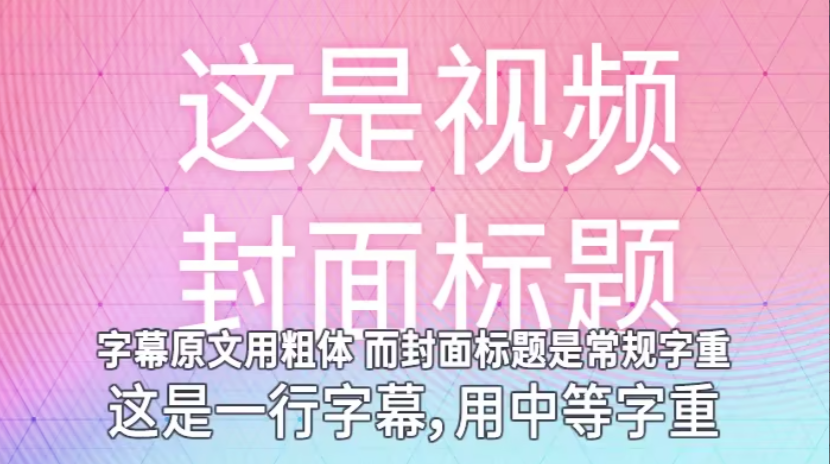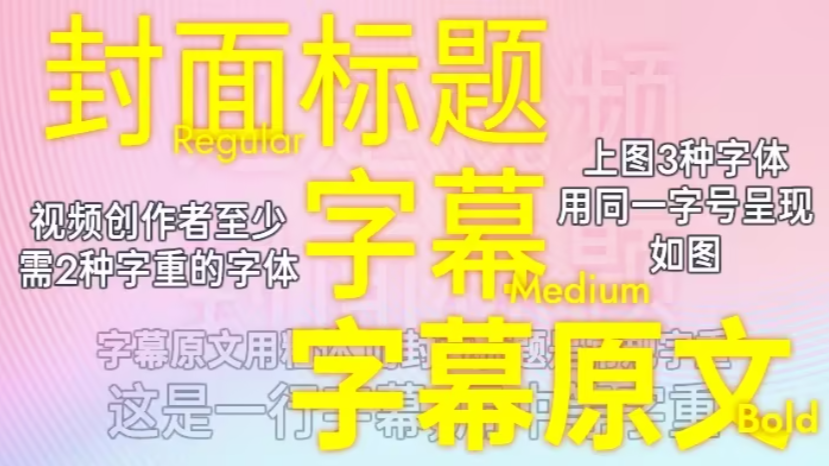
典迹题幕(MonuTitl)是一套专为横排标题和字幕设计的免费开源窄黑体中文字体。包含三个字重,分别是窄体宜读(Condensed Book,近似常规Regular)、窄体中粗(Condensed Medium)和窄体粗体(Condensed Bold)。
典迹题幕的窄体设计使得字体在视觉上看起来更加紧凑,一行内容可以容纳更多文字,非常适合视频字幕那种不用换行的情景。另外,典迹题幕还对标点符号和数字进行了优化,使其能够适应更多不同的应用场景。